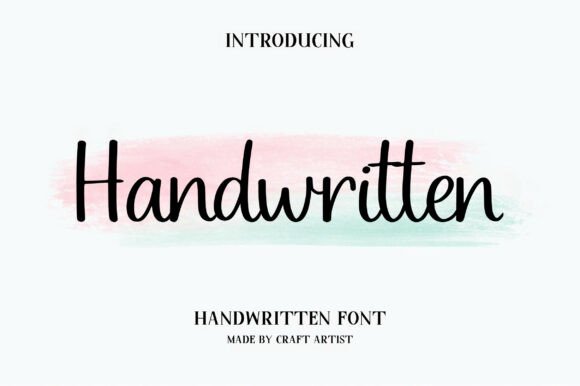
Handwritten : L'Équilibre Parfait entre Élégance Moderne et Naturalité
À la recherche d'une typographie qui apporte une touche humaine et sophistiquée à vos créations ? Découvrez Handwritten, une police de caractères cursive moderne qui capture l'essence même de l'écriture manuscrite avec une fluidité douce et naturelle. Loin des scripts rigides, Handwritten offre un rendu organique qui transforme instantanément n'importe quel design en une pièce unique et stylée.
Ce qui rend Handwritten si spéciale, c'est sa capacité à conjuguer le charme romantique et la clarté contemporaine. Que vous souhaitiez exprimer de la tendresse, du luxe ou une simplicité décontractée, cette police s'adapte avec aisance pour donner un aspect "fait main" tout en restant parfaitement lisible et professionnelle.
Pourquoi choisir la police Handwritten pour vos projets ?
L'utilisation d'une police script bien choisie peut radicalement changer la perception de votre marque. Handwritten est l'outil idéal pour ceux qui veulent sortir du lot avec un style raffiné sans paraître trop formel. C'est le choix parfait lorsque vous recherchez un design qui semble chic, élégant, mais sans effort.
Des applications créatives illimitées
Grâce à sa polyvalence, Handwritten s'intègre harmonieusement dans une multitude de supports. Voici quelques idées pour exploiter tout son potentiel :
- Branding & Logos : Créez une identité visuelle mémorable et personnelle.
- Événements : Idéale pour des invitations de mariage, des faire-part ou des cartes de vœux romantiques.
- Marketing Digital : Sublimez vos publications sur les réseaux sociaux (Instagram, Pinterest) et vos citations inspirantes.
- Mode & Beauté : Parfaite pour des lookbooks de mode ou des packagings de produits cosmétiques haut de gamme.
- Supports Promotionnels : Ajoutez une touche de prestige à vos brochures et campagnes de marketing.
Verdict : Le choix idéal pour un design organique
En résumé, si vous voulez insuffler de la vie et de la poésie à vos visuels, Handwritten est la solution. Elle apporte cette note de douceur et de sophistication qui captive l'œil tout en conservant un esprit décontracté. C'est bien plus qu'une simple police ; c'est un véritable atout créatif pour transformer vos idées en chefs-d'œuvre visuels.